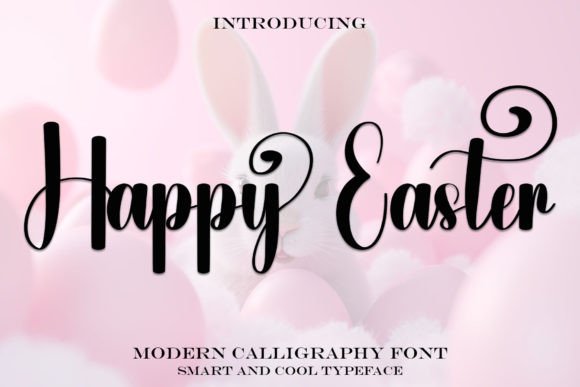
Happy Easter
Jika Anda mencari aset berkualitas tinggi seperti Happy Easter, paket premium ini adalah pilihan fantastis untuk proyek kreatif Anda.
Baik Anda membuat produk POD (Print on Demand), undangan pernikahan, atau grafis media sosial, Happy Easter adalah pilihan yang sangat ideal.